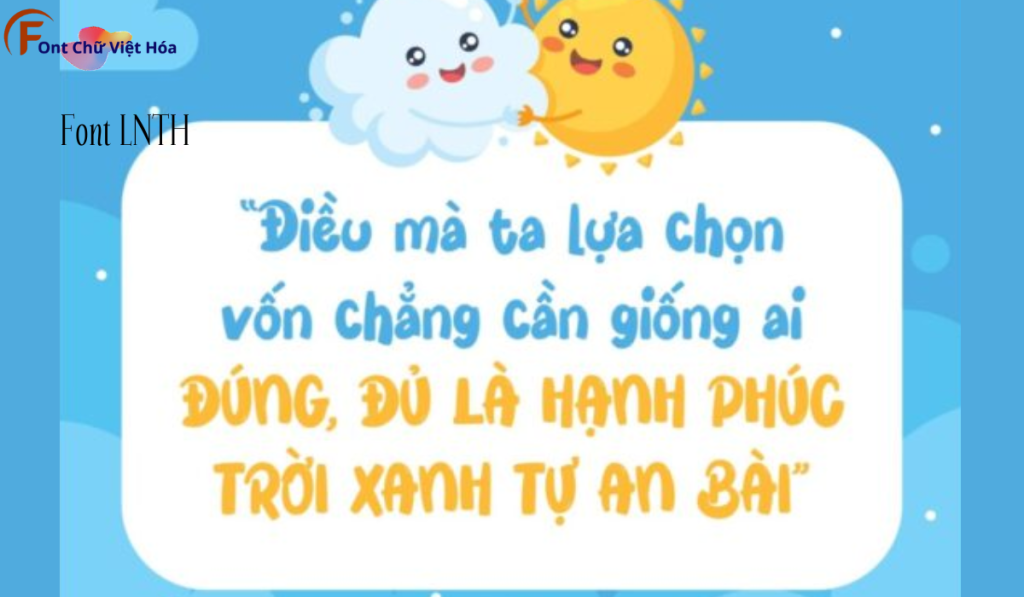
Font LNTH Blue Cheries Việt Hóa
Tác giả: LNTH
Bộ Font: LNTH
Font LNTH Blue Cheries Việt Hóa là một font chữ nghệ thuật, thuộc bộ LNTH, với thiết kế như nét bút lông. Phong cách của font này phù hợp với các dự án thiết kế cần sự nghệ thuật và sáng tạo, như poster, thiệp mời, hoặc bảng hiệu. Font LNTH Blue Cheries Việt Hóa mang đến sự nghệ thuật và dễ nhận diện, ứng dụng trong các lĩnh vực sáng tạo. Đặc điểm hình dạng của font bao gồm các nét bút lông mềm mại và tự nhiên, giúp tăng tính thẩm mỹ và sự chú ý. Việc Việt hóa font giúp người dùng dễ dàng sử dụng trong các thiết kế tiếng Việt, mang lại sự tiện lợi và linh hoạt.